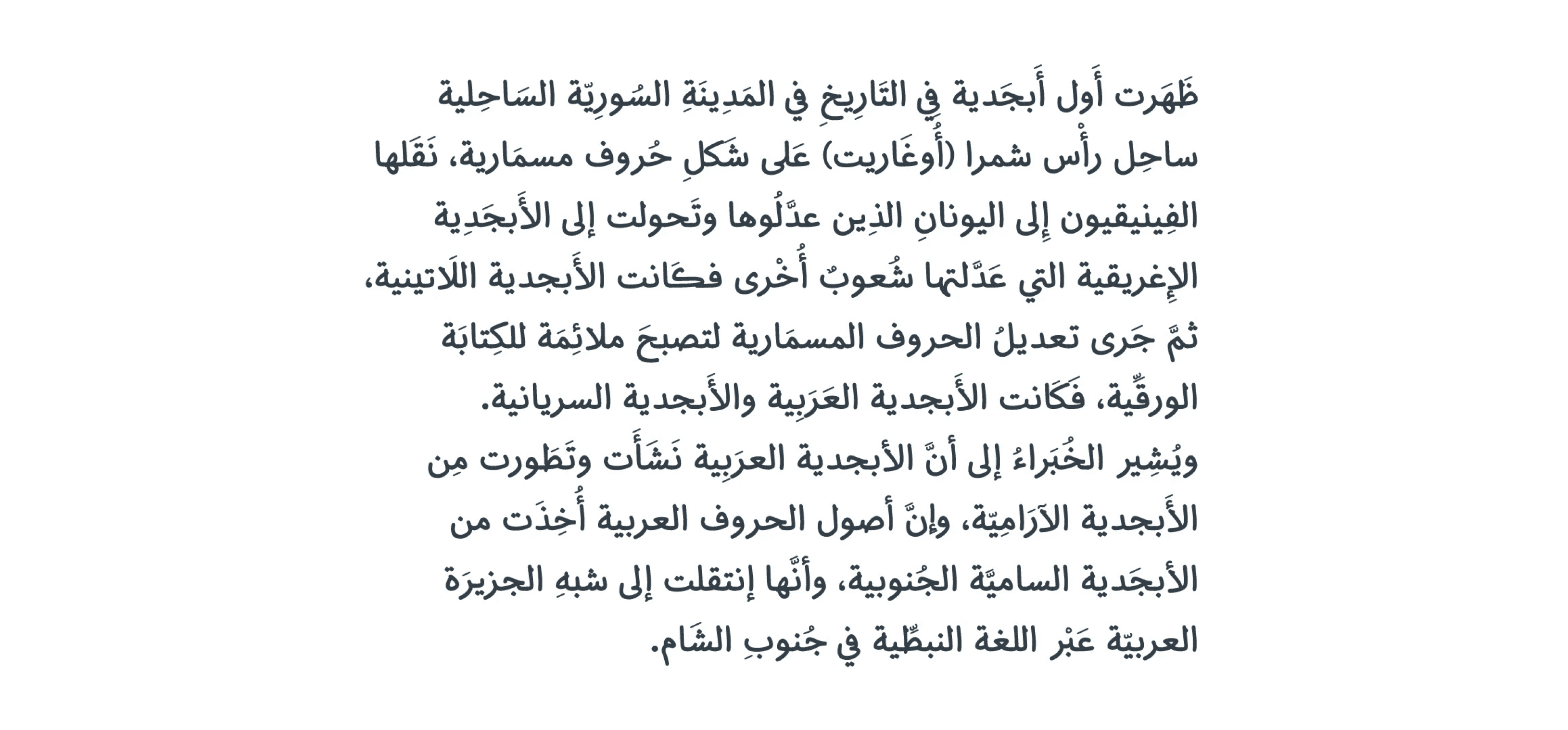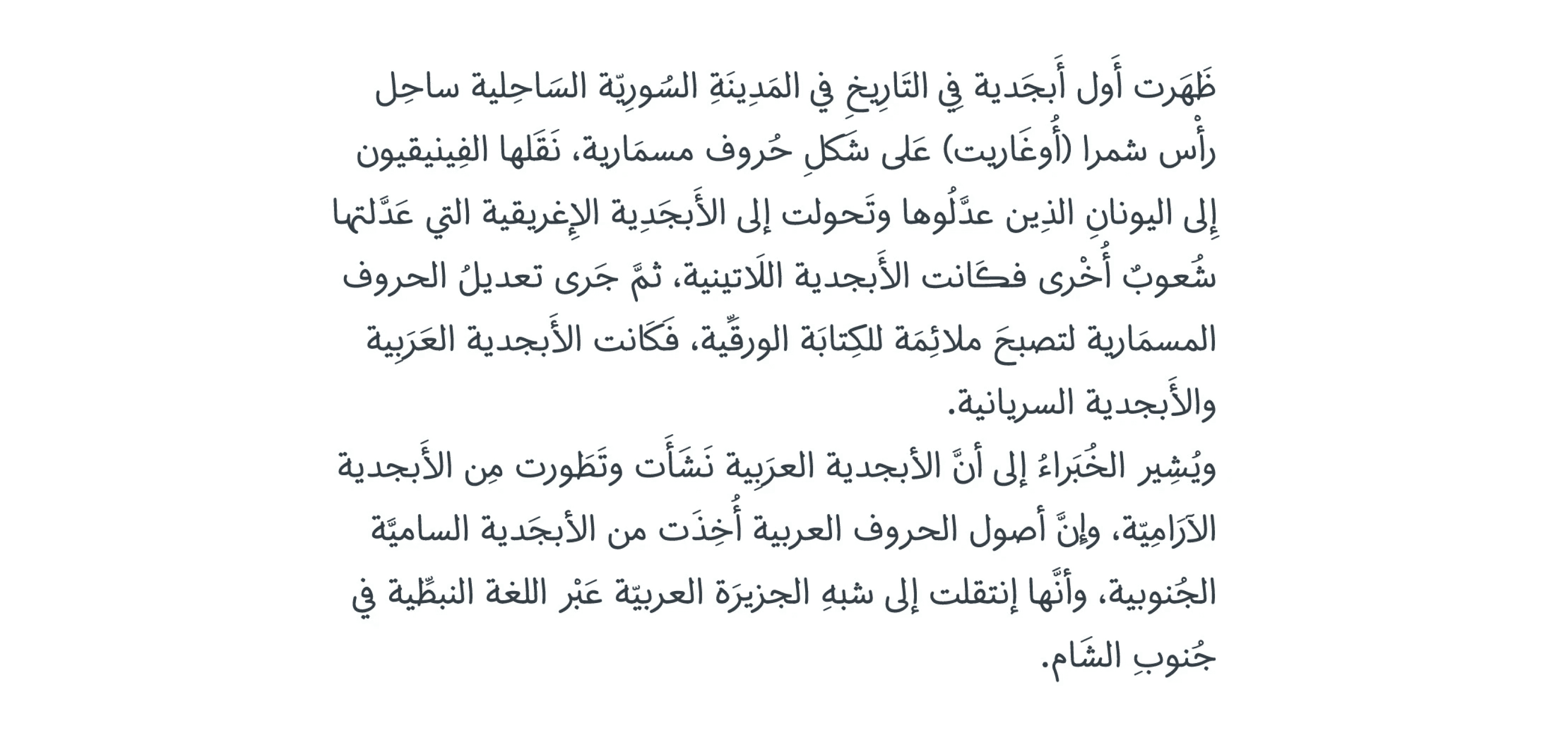
الخط JH Roy هو خط عربي بأسلوب النسخ اليدوي، ويتضمن وزنين. يُعد مناسبًا للنصوص الطويلة، العناوين، الهوية البصرية، واللافتات...
تم ضبط مواضع التشكيل بدقة لتلبية متطلبات الناشرين.